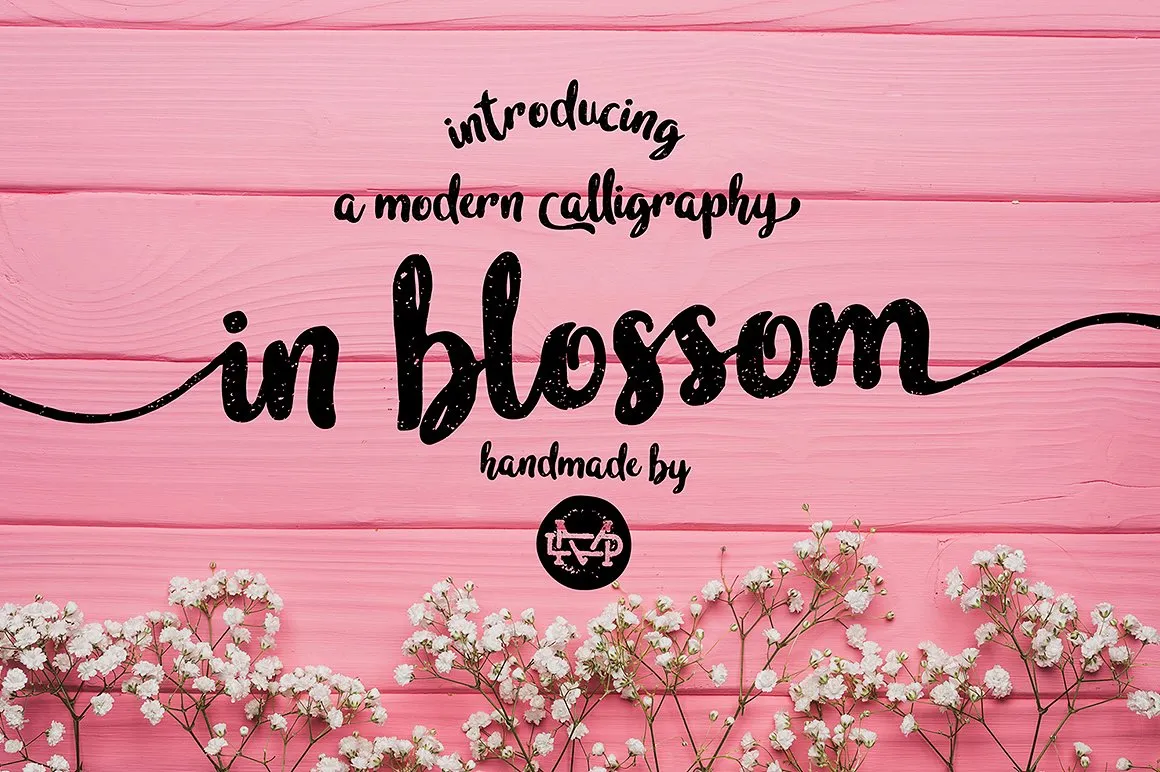
In Blossom Script Font – Fonte Grátis
In Blossom Script Font
Bem-vindo à descoberta de “In Blossom Script Font”, uma elegante fonte script que irá transformar qualquer projeto gráfico em algo especial e envolvente. Criada por madeDuk, essa font é ideal para quem busca um estilo delicado e sofisticado para nomes ou marcas. Se você adora as nuances de uma letra escrita a mão, este é seu tipo perfeito. Com sua tipografia fluida e detalhada, “In Blossom Script Font” permite que suas criações transmitem sensibilidade e elegância através dos traços delicados do papel. Quer usar essa fonte para um projeto de identidade visual ou apenas adicionar um toque artístico a seu trabalho? Estamos felizes em oferecer esta demo gratuita como uma maneira de você explorar as possibilidades deste belo design. Mas se desejar o uso completo dessa maravilhosa font, basta clicar na ligação que está disponível abaixo. Descubra e explore os incontáveis usos para esta “In Blossom Script Font”. Eles não apenas são úteis em projetos de identidade visual, mas também podem fazer uma declaração única em qualquer tipo de projeto.